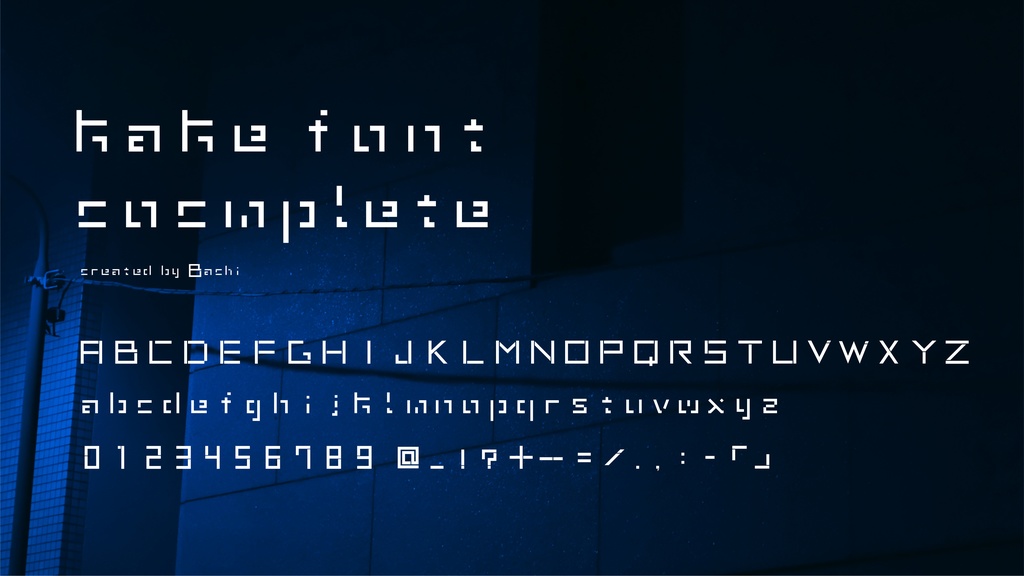
kake font complete
ほんの少し欠けた欧文オリジナルフォント、「kake font」のコンプリート版です。大文字、小文字、数字、常用記号(数点)になっています。 「kake font complete」 →内容物:TTF、OTF、イメージJPG、利用規約 「利用規約テキスト」 →内容物:利用規約※ ※更新前のデータをダウンロードした方で、利用規約のテキストデータをお持ちでない方は、適宜ダウンロードいただけますと幸いです。 ********* フォント利用規約をNotionページにて一元管理する形に変更しました。 最新の規約は以下URLよりご確認ください。 ▼ライセンスページ https://sustaining-museum-4c0.notion.site/3283407b3a088018a67ad3511048bf6a?source=copy_link ********* フォントのインストール、ソフト上の使用サポートやお問い合わせはお受けできません。あらかじめご了承ください。 その他、権利、規約に関するお問い合わせは、以下のお問い合わせにてご連絡ください。 【お問い合わせフォーム】https://monadesign.studio.site/contact ※上記記載内容は予告なく変更する場合がございます。あらかじめご了承ください。(2026.3.23更新)